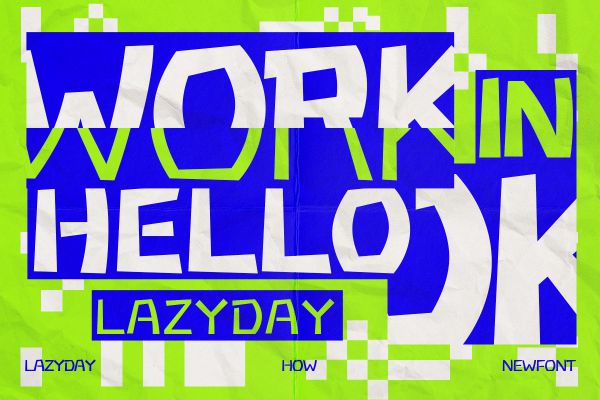
AiDeep
AiDeep是一款专为标题设计打造的英文Display字体,融合现代简约与趣味设计美学。字体采用方正结构设计,字体重心居中,中宫比例适中,展现出端庄稳重的视觉气质。笔画以粗体均匀呈现,方头笔型搭配精准斜切处理,在直角线条中融入微妙的角度变化,既保留几何美感又增添设计巧思。 AiDeep作为免费商用字体,适用于品牌标识、广告海报、包装设计等视觉传达场景,其断开式笔画连接设计能有效提升文字的识别度与视觉张力。字体包含26个大小写英文字母及10位阿拉伯数字,虽字符集精简但满足英文标题与数字信息的基础排版需求,是现代设计项目中兼具实用性与个性表达的理想选择。